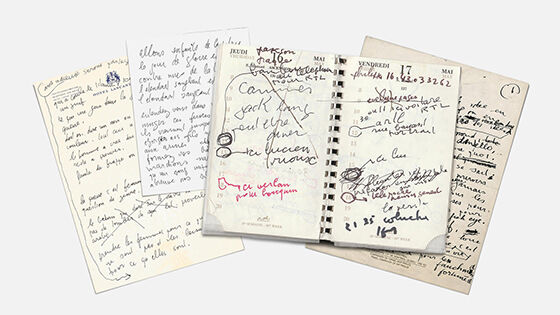
Download di Sini! 5 Font Unik dari Tulisan Tangan Musisi Terkenal di Dunia
Buat kamu para penikmat musik, ada loh 5 font unik yang terinspirasi dari tulisan tangan para tokoh musisi terkenal di dunia. Siapa sajakah mereka?
5 Font Unik dari Tulisan Tangan Musisi Terkenal di Dunia
Baru-baru ini, sebuah website bernama Songwriters Font merilis 5 jenis font yang terinspirasi dari musisi terkenal di dunia, tentu dengan karya yang nggak asing di telinga kamu loh!
Proyek ini sendiri digawangi oleh desainer grafis asal Prancis, Nicolas Damiens bersama dengan Julien Sans yang berprofesi sebagai seorang copywriter. Nah penasaran gimana keunikannya? Eh ya, jangan sampai lupa download guys!
1. Kurt Font (Kurt Cobain)
Kurt Cobain adalah punggawa sekaligus vokalis dari grup band Nirvana yang dibentuk pada 1987. Nirvana yang memiliki genre music grunge ini terinspirasi dari sosok Kurt Cobain yang menyukai music punk rock, blues dan heavy metal loh!
Sample Kurt Font
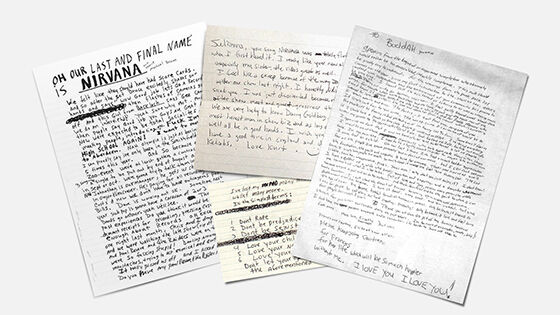
2. David Font (David Bowie)
Selanjutnya ada legenda musik asal Inggris, David Bowie yang lahir di Brixton, London Selatan pada 1947 silam. Bakat David Bowie memang sudah terasah sejak mempelajari seni, musik dan desain. Karya yang paling terkenalnya berjudul Space Oddity pada tahun 1969.
Sample David Font
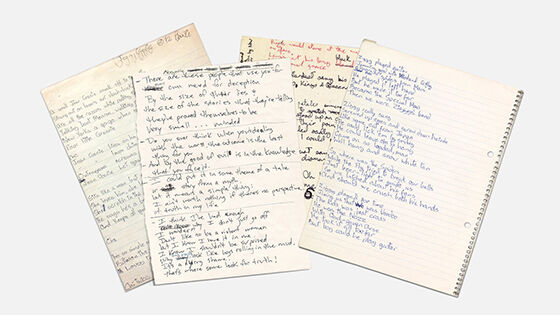
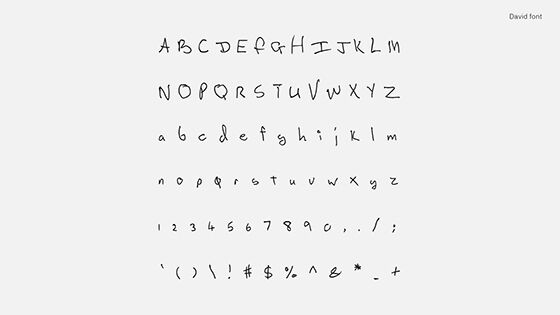
3. John Font (John Lennon)
Satu lagi musisi ternama asal Inggris masuk ke dalam daftar Songwriters Fonts. Siapa lagi kalau bukan John Lennon yang membentuk grup band The Beatles bersama Paul McCartney, George Harrison dan Ringo Starr. Tentu kamu nggak akan asing dengan lagu mereka, kan?
Sample John Font
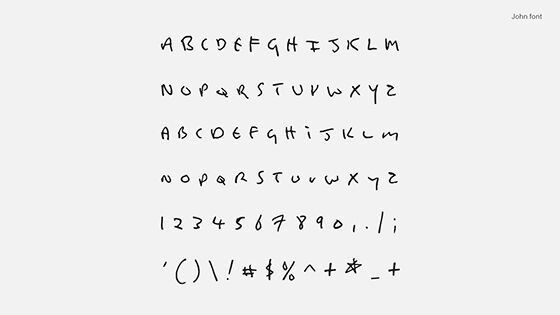
4. Leonard Font (Leonard Cohen)
Berawal dari menciptakan puisi dan novel, Leonard Cohen pun akhirnya menjadi seorang penulis musik sekaligus penyanyi. Pria kelahiran Kanada ini memulai debut album berjudul Songs of Leonard Cohen pada tahun 1967 silam.
Sample Leonard Font
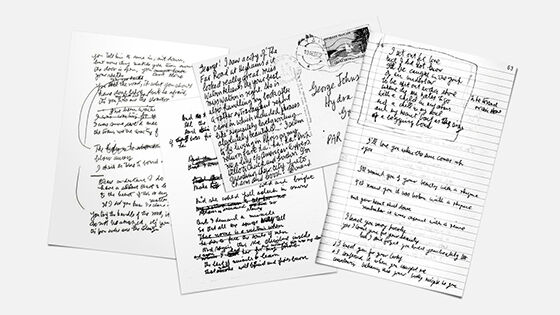
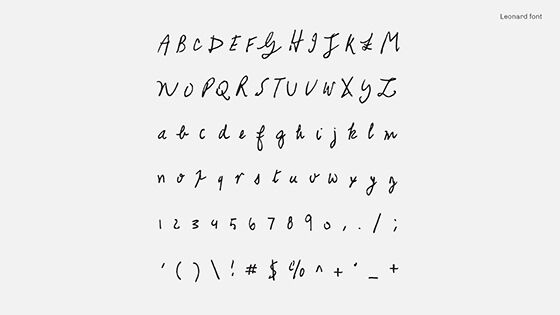
5. Serge Font (Serge Gainsbourg)
Selain terkenal sebagai penulis lagu terbaik asal Prancis, Serge Gainsbourg merupakan seniman, mulai dari penyanyi, pembaca puisi, komposer, pelukis, penulis naskah film dan aktor. Karyanya pun sangat terkenal karena berisi satire dan provokatif.
Sample Serge Font